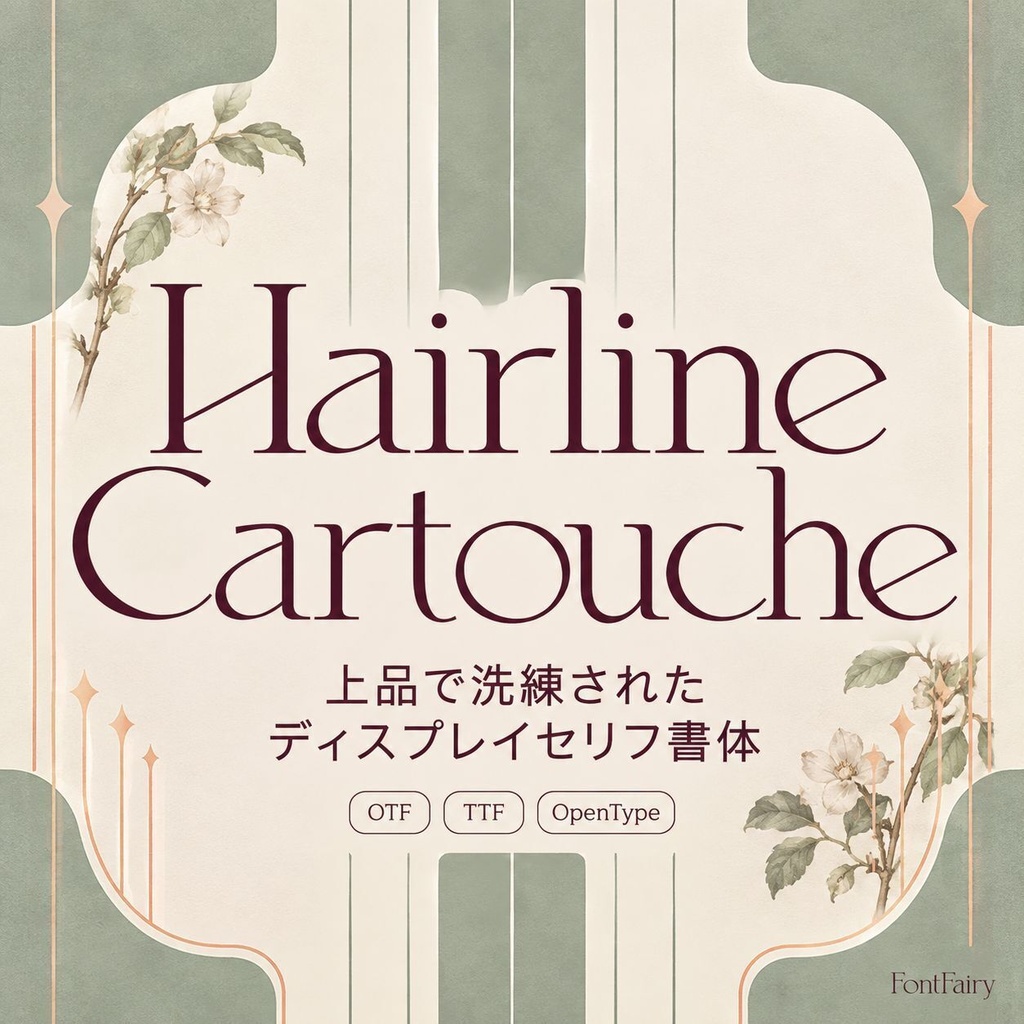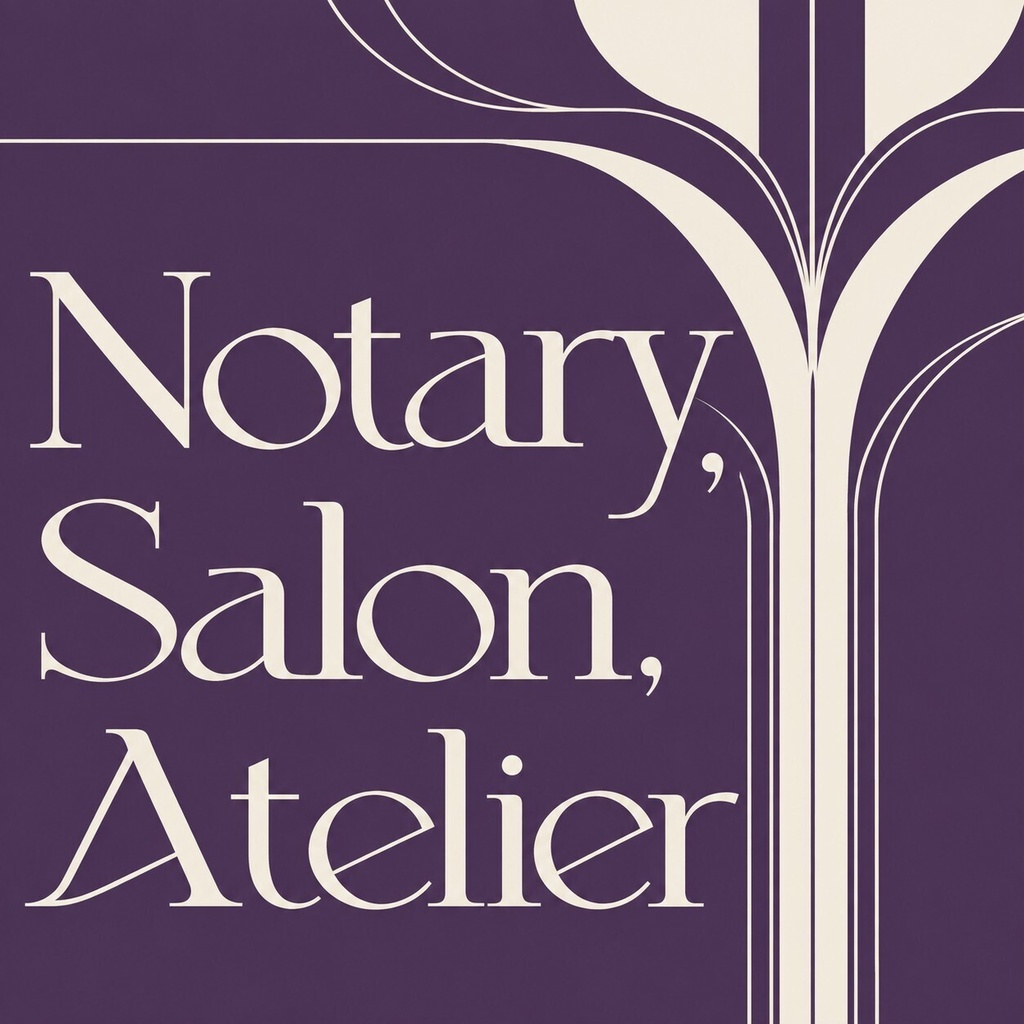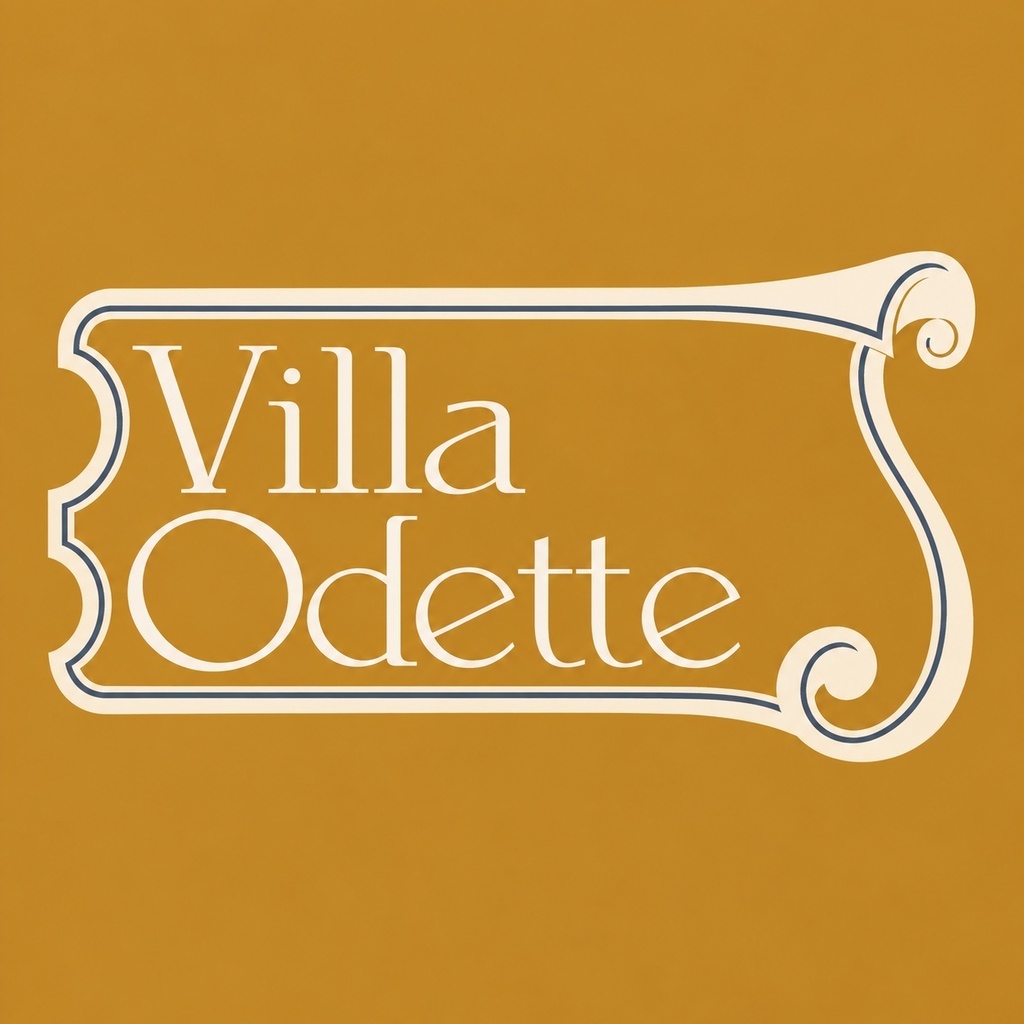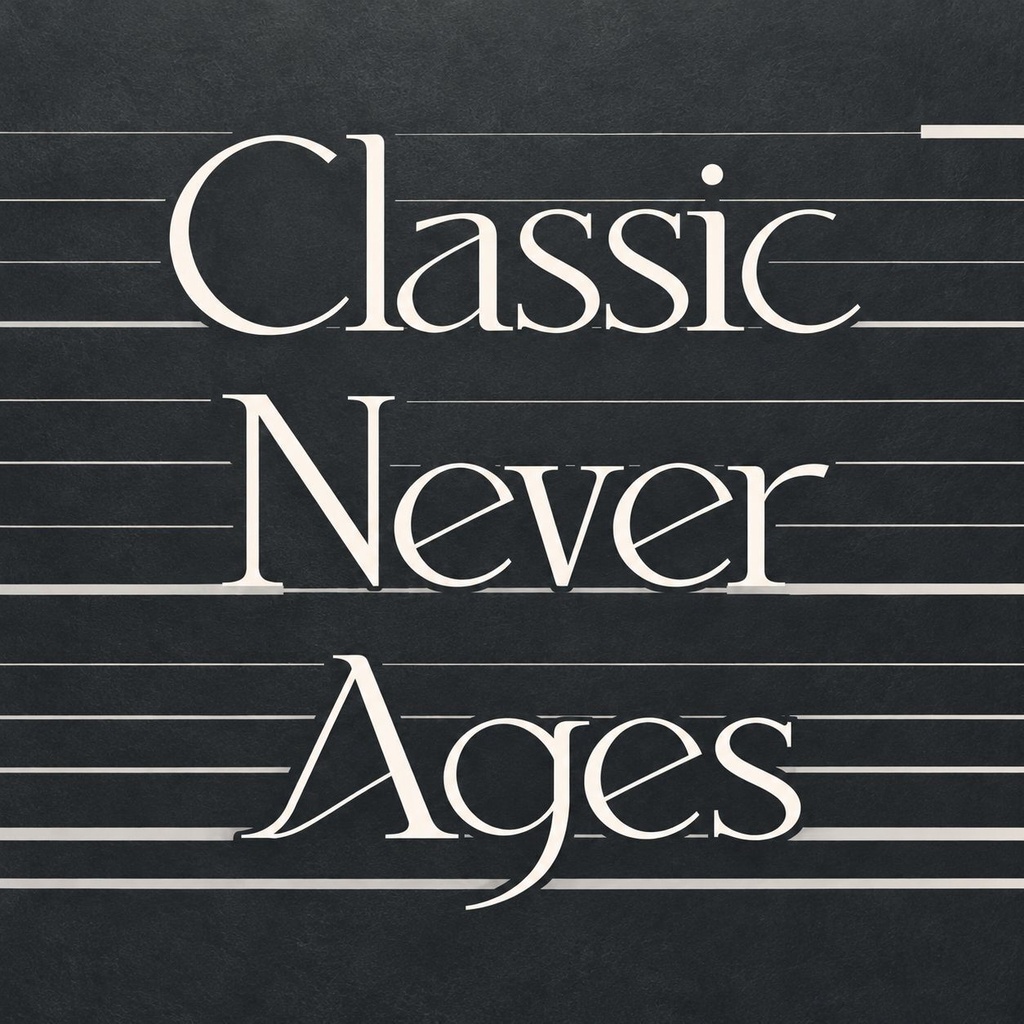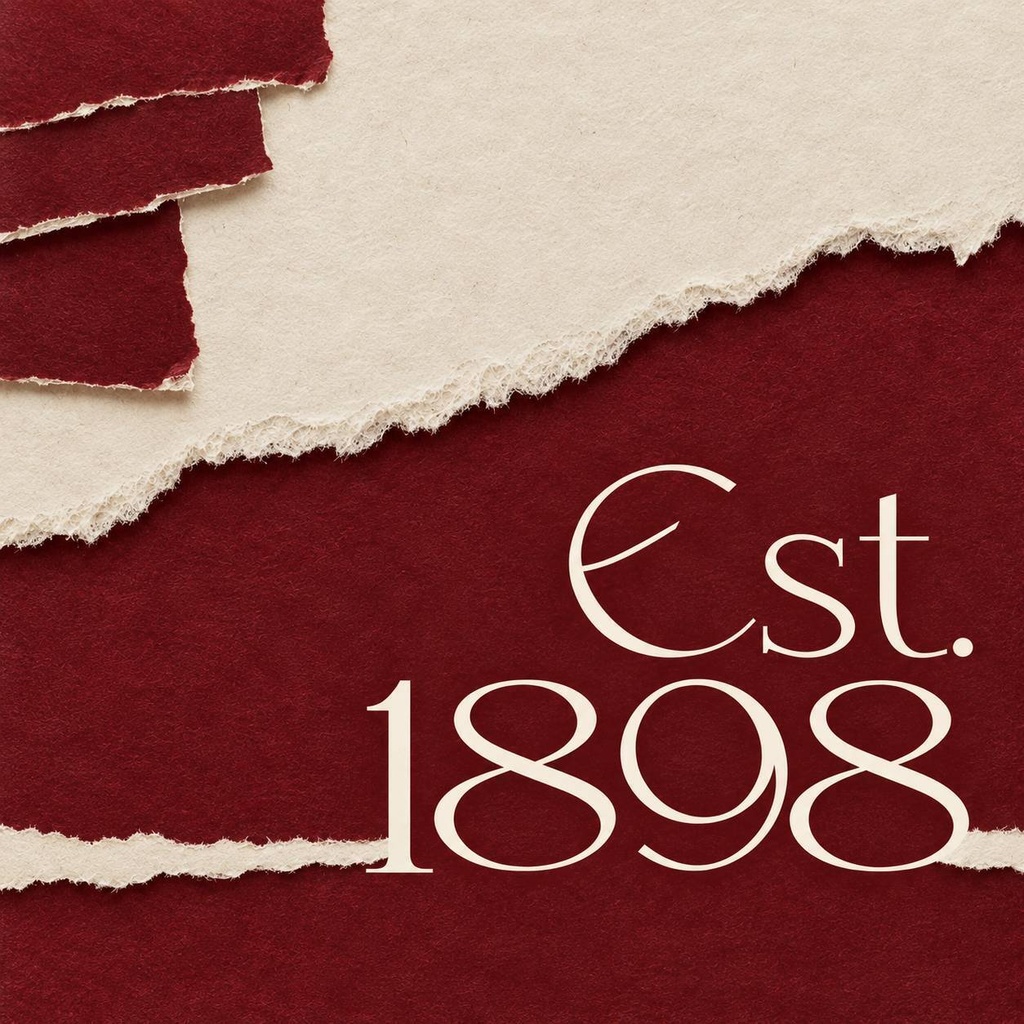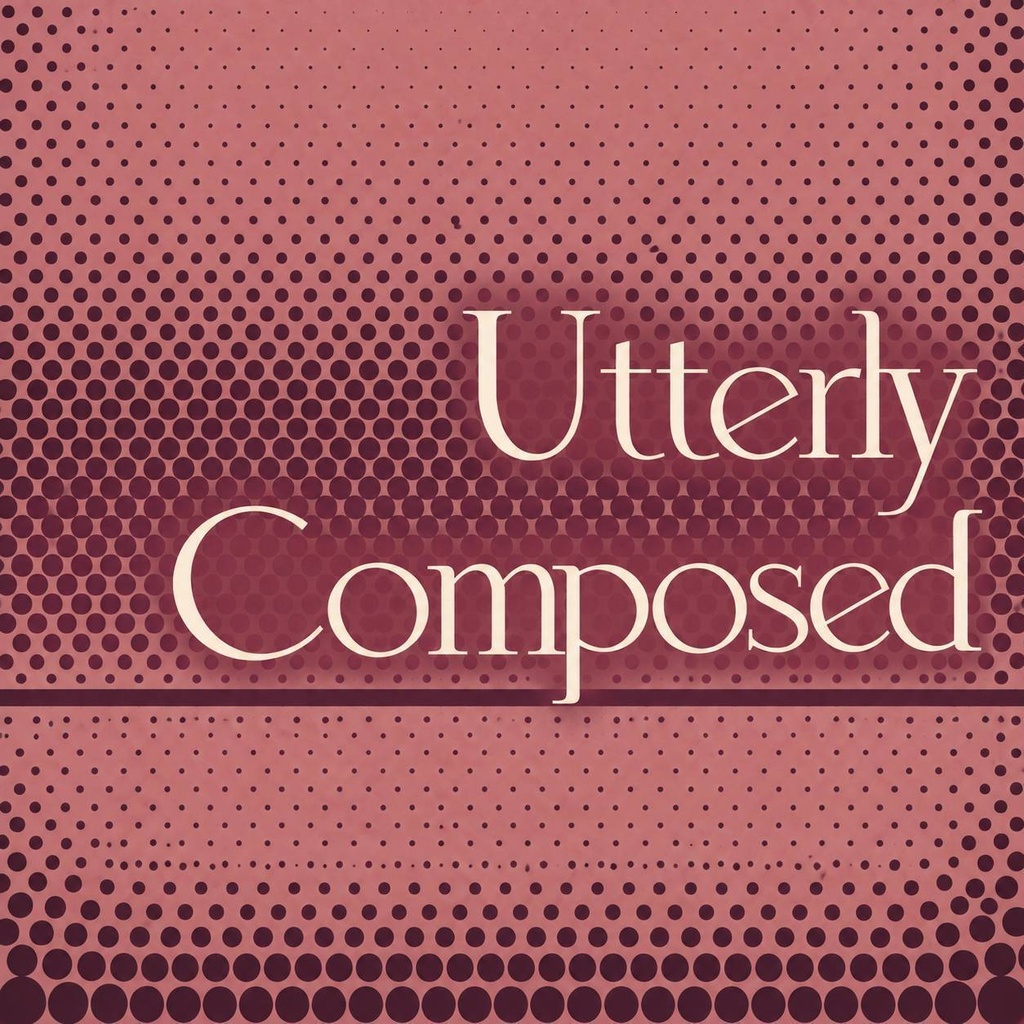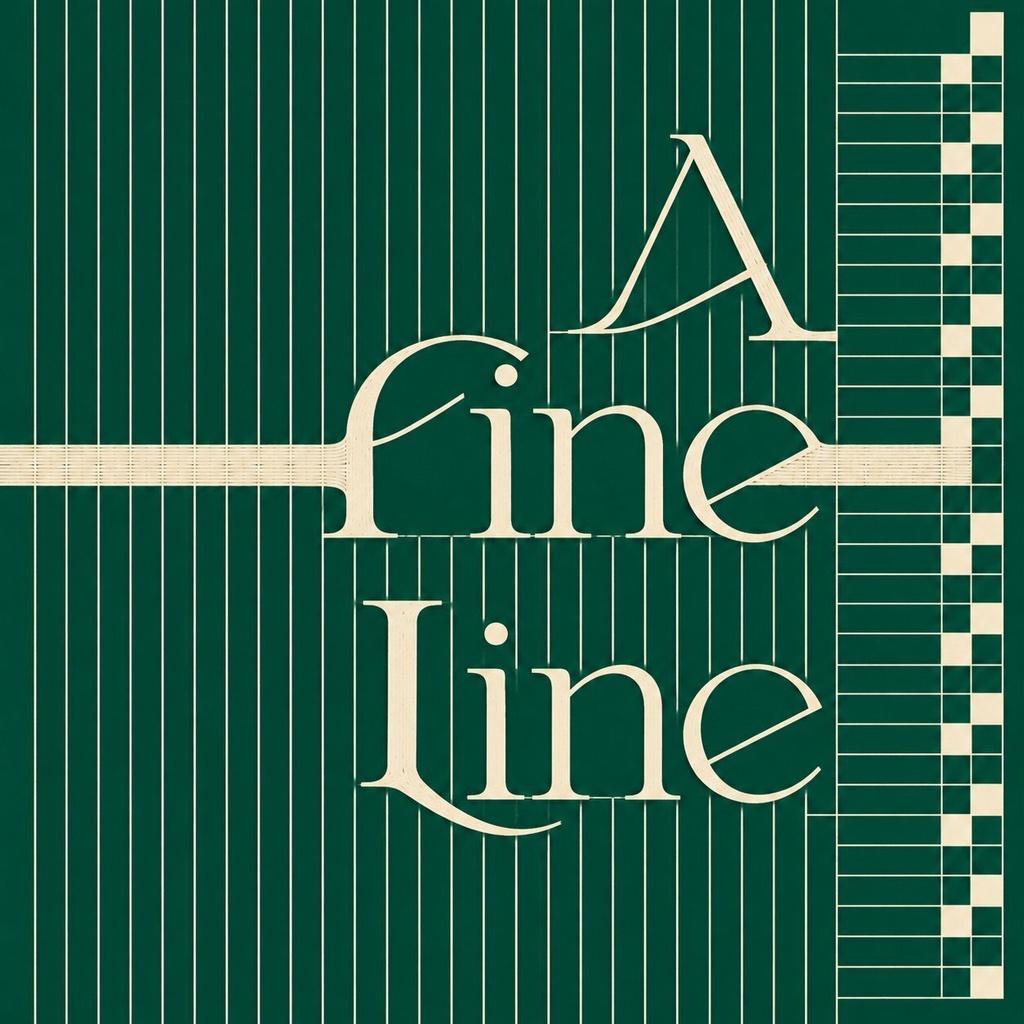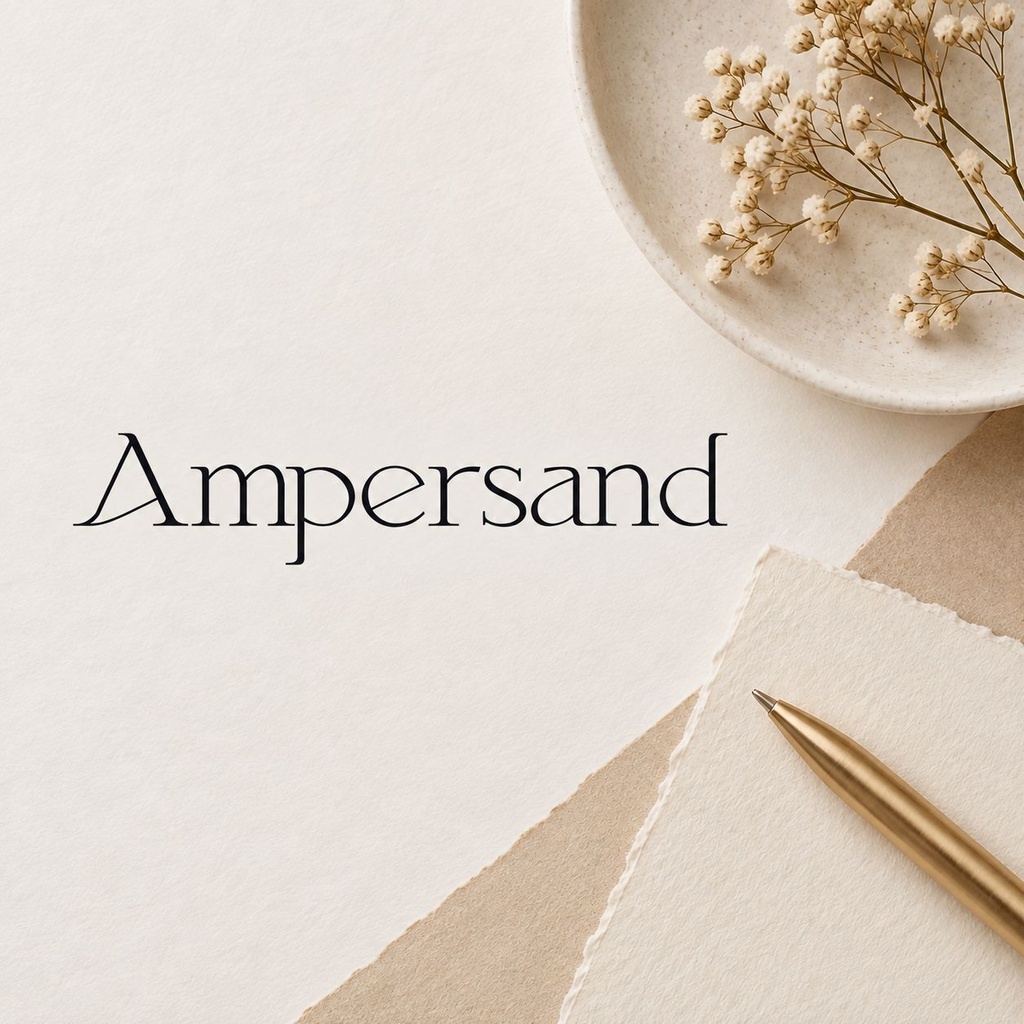
【期間限定無料】Hairline Cartouche(ヘアライン・カルトゥーシュ)を、期間限定キャンペーン中は無料でダウンロードできます。無料で使えるのは期間限定の「無料デモ」で、商用利用を含む「フルバージョン」は有償ライセンスのままです。 しなやかな曲線と繊細なコントラストが美しい、シックでエレガントなセリフ欧文フォントです。ロゴ、見出し、引用文(クォート)、職種や業種を伝えるプロフェッショナルな表現、Webページの見出しなど、上品でクラシックなタイポグラフィを求める制作に寄り添います。大文字と小文字、数字、記号、リガチャー(合字)まで収録し、エレガントな雰囲気をそのまま文字にできます。 期間限定の無料キャンペーン中です。上の「無料デモ」からダウンロードできます。ダウンロードしたら、ぜひBOOTHで「いいね」・お気に入り登録をお願いします! 【収録内容】 ・フォントファイル(OTF / TTF / WOFF / WOFF2) ・大文字・小文字(A–Z / a–z) ・数字・記号・句読点 ・リガチャー(合字)— Adobe Illustrator(イラレ)では「書式」→「字形」パネルから切り替えられます 【対応文字】 ・欧文(ラテン文字)の大文字・小文字、数字、記号・句読点 ・多言語のアクセント付き文字に対応 ・日本語・キリル文字・ギリシャ文字は収録されていません 【用途】 ・ロゴ・ブランドマーク ・見出し・タイトル ・引用文・キャッチコピー ・職種・業種を伝えるプロフェッショナルなデザイン ・Webページの見出し(WOFF / WOFF2 を収録) 【形式】 ・OTF(OpenType) ・TTF(TrueType) ・WOFF(Web Open Font Format) ・WOFF2(Web Open Font Format 2) 【対応環境】 ・macOS / Windows ・Adobe Illustrator(イラレ)など字形パネルに対応したアプリで、リガチャー(合字)を切り替えられます ・Webフォントとしても使えます。Webページでは WOFF / WOFF2 をそのまま読み込めます ・リガチャーに対応していないアプリでは、通常の字形で表示されます 【利用許諾】 ・フルバージョン(Full Version)は商用利用可(Commercial Use)。ビジネス・クライアントワーク・有料・ブランド化・広告・グッズ制作などに使用できます ・無料デモ(Free Demo)は期間限定で無料。購入者自身の非商用プロジェクト・学習・練習・プライベート制作に使用できます ・商用利用は「フルバージョン」に含まれます。「無料デモ」には含まれません ・フォントファイルの再配布・再販売はできません(許諾範囲の詳細は付属のライセンスファイルをご確認ください) ・「この使い方は商用になる?」と迷う用途は、ご購入前にお問い合わせください ・本フォントの著作権は FontFairy に属します 期間限定の無料キャンペーンは、終了日が決まりしだい終了します。「無料デモ」で気に入ったら、そのままフルバージョンへ。ダウンロードの際は、ぜひBOOTHで「いいね」・お気に入り登録をお願いします!